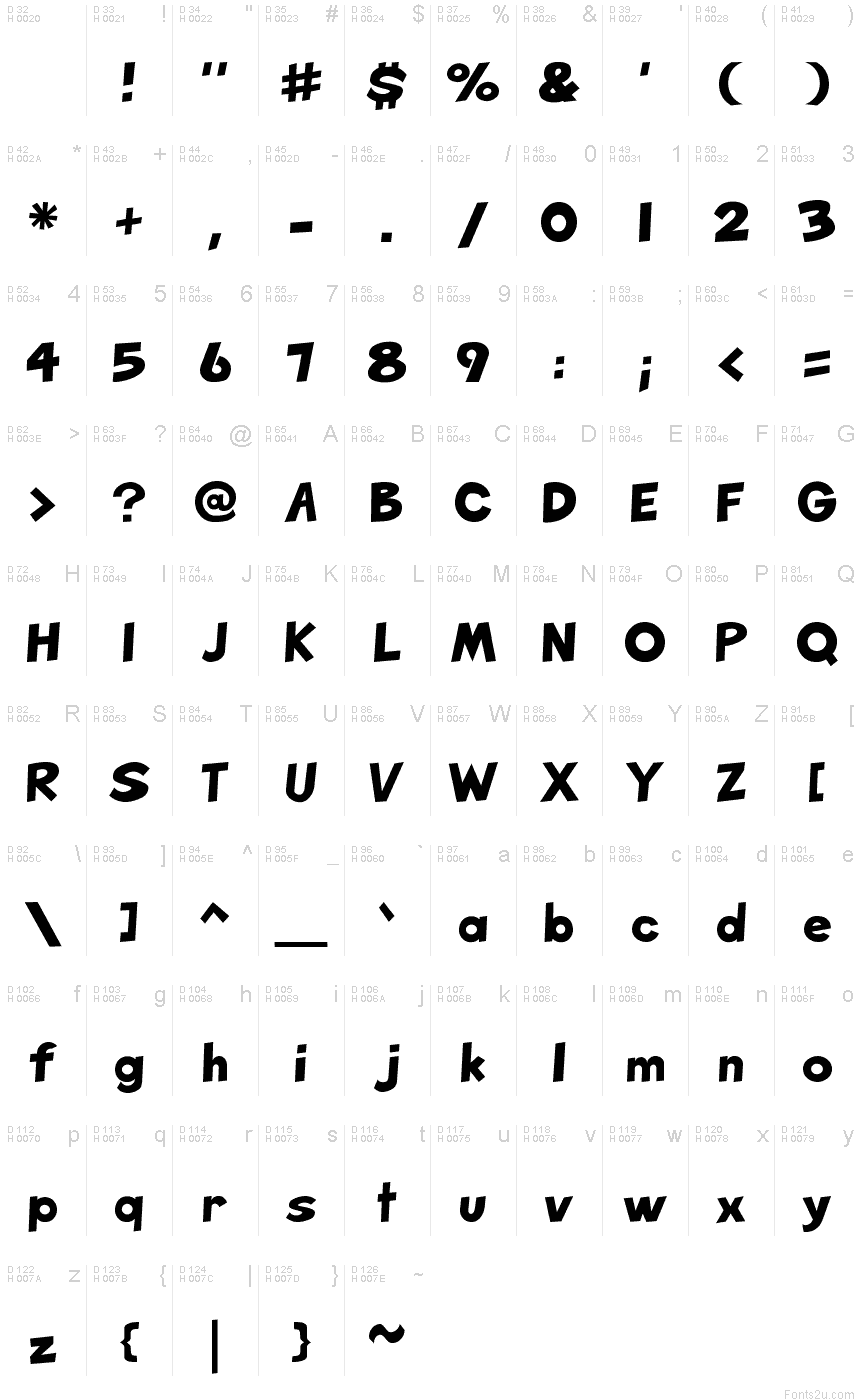
Mettler to darmowy font typu display w stylu kreskówkowym. Masywne, pochylone litery nadają mu głośnego i zabawnego charakteru już na pierwszy rzut oka. Litery wyróżniają się sporą grubością i wyrazistymi, niemal wycinankowymi kształtami, a zaokrąglone „e” sprawia, że font nie wydaje się zbyt toporny czy surowy.
Świetnie sprawdza się w nagłówkach plakatów, dziecięcym brandingu, komiksowych opakowaniach, ulotkach czy odważnych grafikach do mediów społecznościowych, gdzie krótkie hasło powinno przyciągać wzrok. Jako darmowy font, Mettler doskonale nadaje się też do tytułów i chwytliwych nagłówków, bo jego ciężki, nieco zadziorny styl dodaje tekstom życia i dynamiki.
Mettler